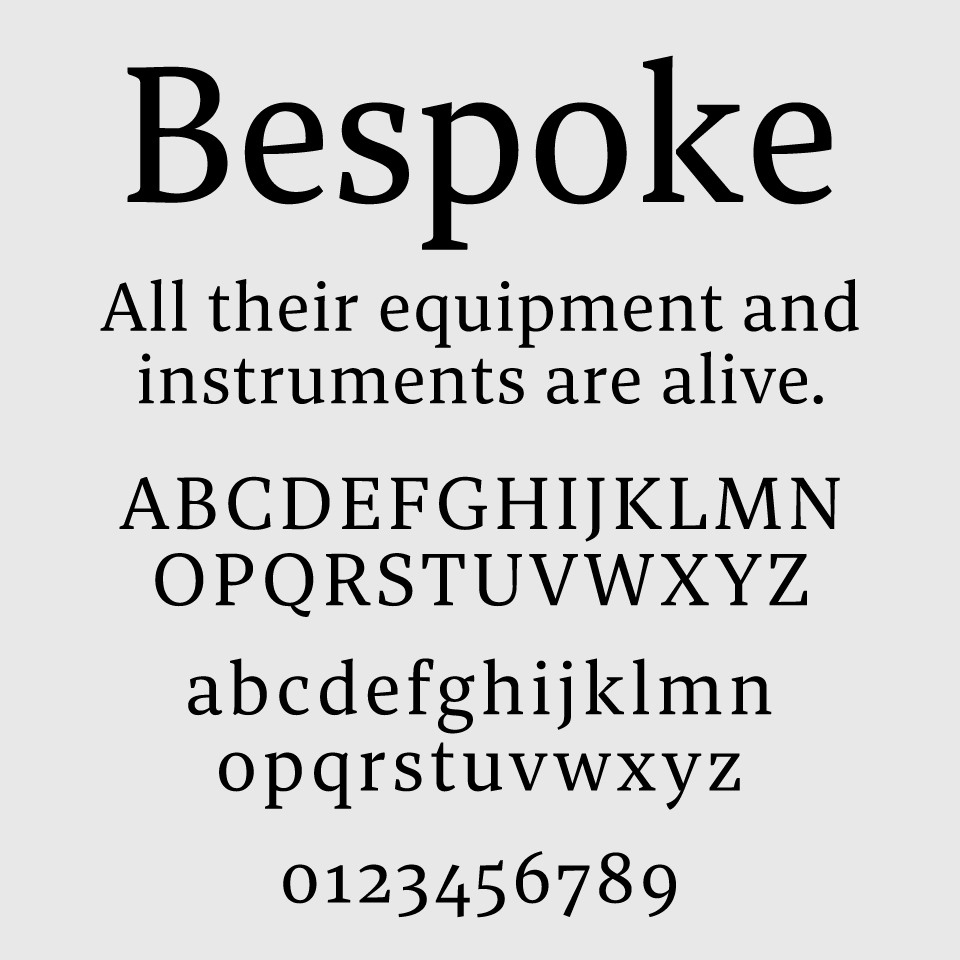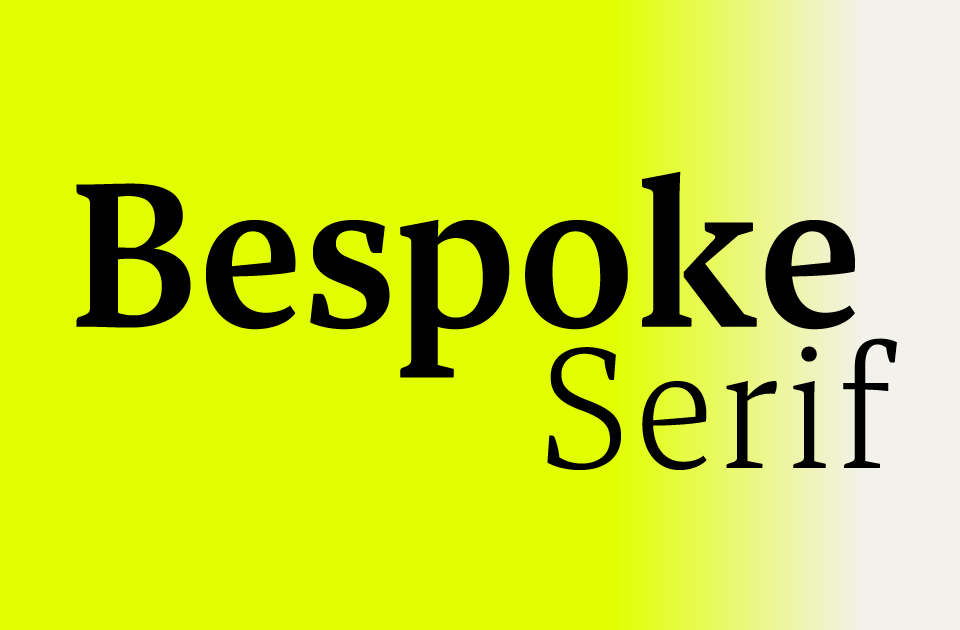
Bespoke Serifフォントは、クラシカルな格調高さと温かみが同居したセリフ体フォントです。
アルファベットの端々に施された微細なカーブや、不均一なストロークの太さが、無機質になりがちな活字に独特の親密さを与えています。洗練されたセリフ体ながら、どこか人の手によるぬくもりを感じさせる佇まいが特徴です。
個性がありながらも主張しすぎないため、本文用にもタイトル用にも使いやすいフォントです。